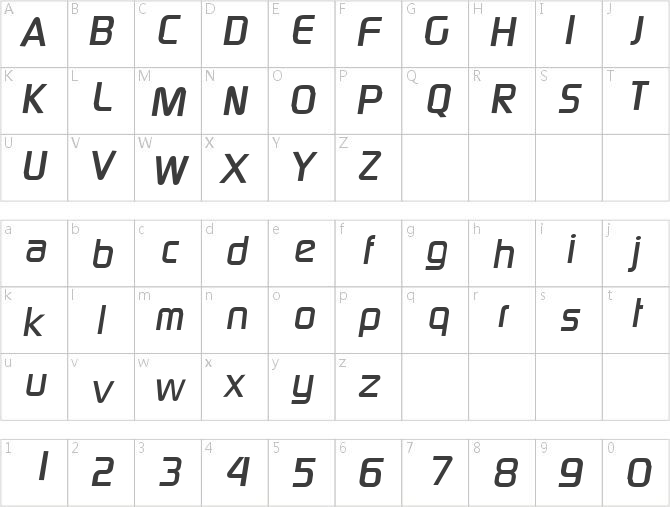
prisonersfitalic
prisonersfitalic介紹
prisonersfitalic字體字庫(kù)是一款讓人賞心悅目、百看不厭的英文字體,適合各類廣告和產(chǎn)品包裝設(shè)計(jì)應(yīng)用,字體大小0.05MB,格式為ttf字體,上傳用戶是快霸中國(guó),作者/版權(quán)方為未知